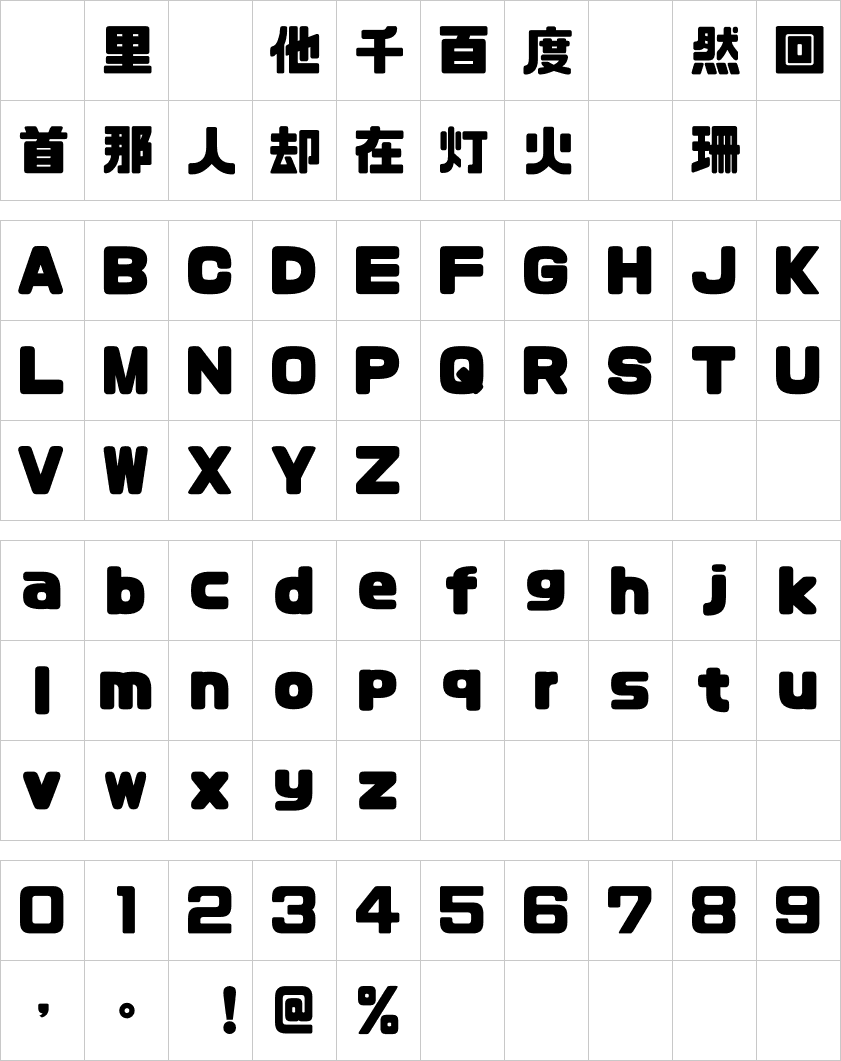
检查站字体チェックポイントフォント
检查站字体(日文名:チェックポイントフォント)是从日本网站“よく飛ばない鳥”上转载回来的。虽然这是一款日本设计师制作的字体,但是所包含的中文字型还算比较多的。其中含JIS第1水准2965字,第2水准3390字+IMB扩张字体+日本教育汉字等,约6900个中文字。而且是可以免费商用无限制。
这款字体比较有日本特色,是日本街头招牌特色字体。